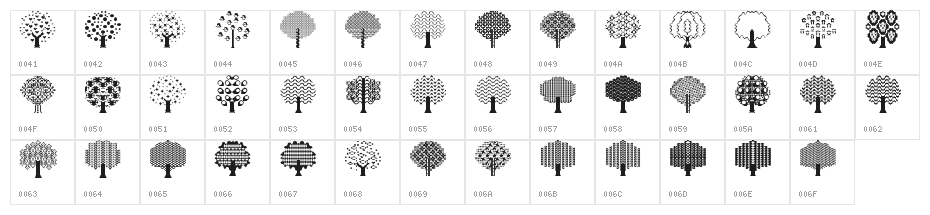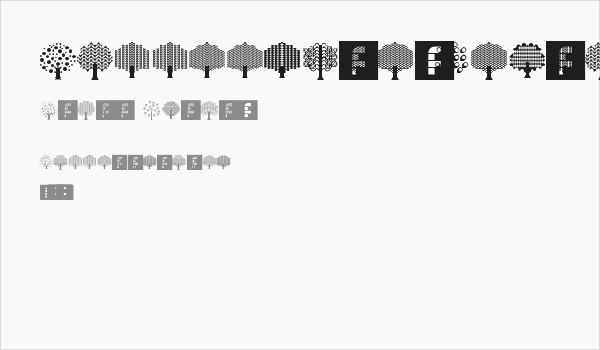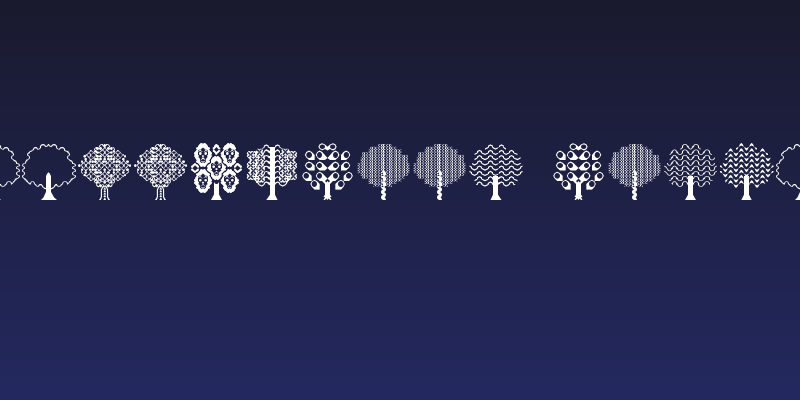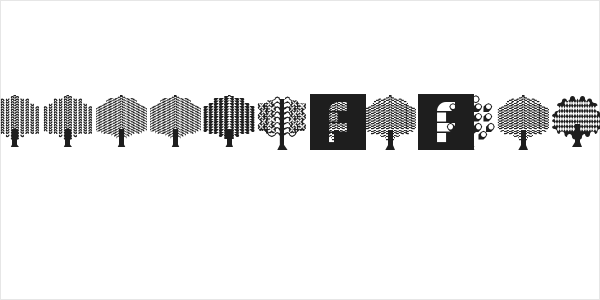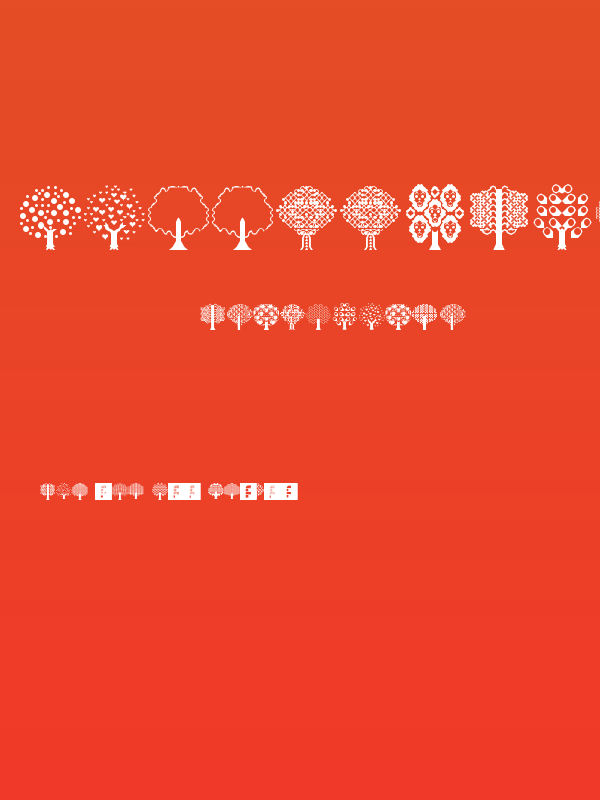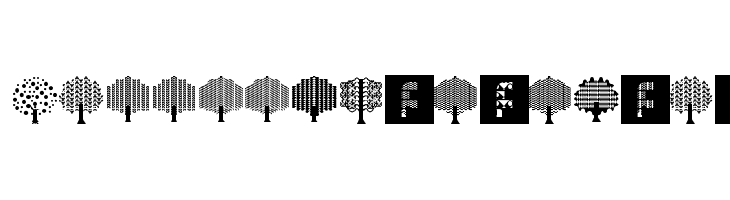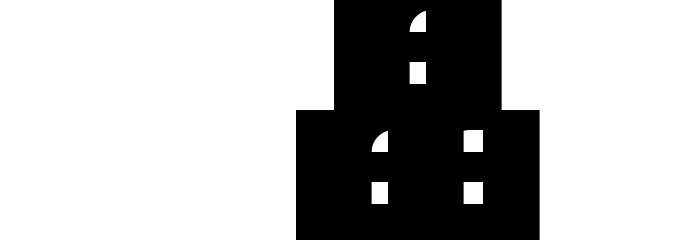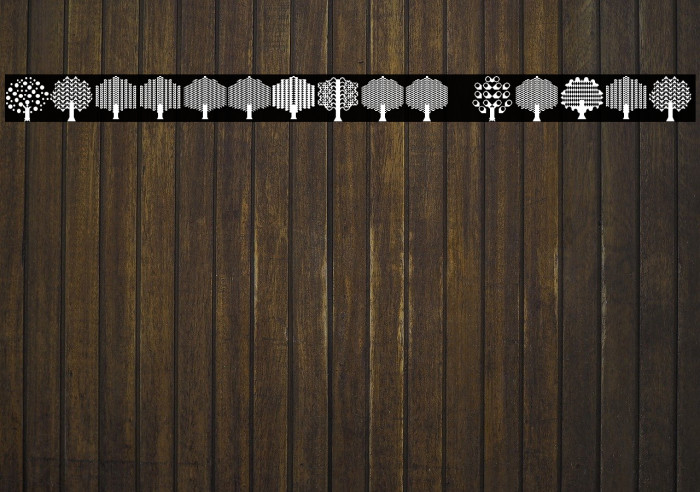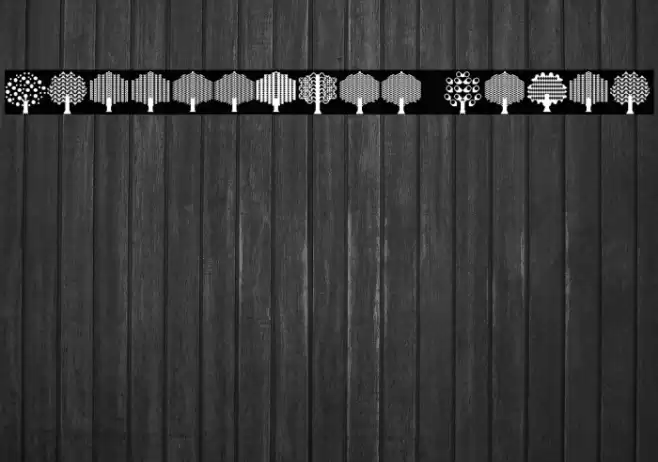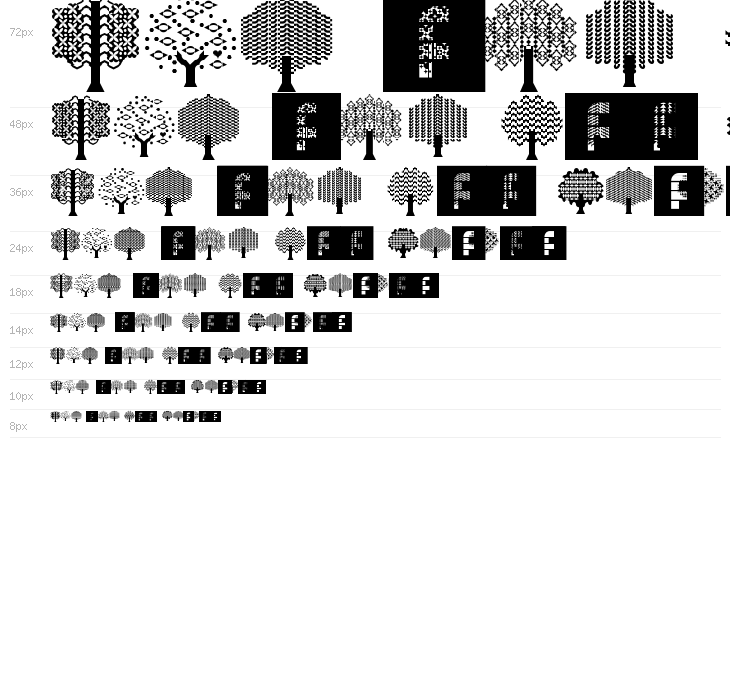
BalloonTrees Regular Font
| Gesamtstil | Decorative, Playful, Graphic |
| Anwendungsfall | Icons, Decorative elements, Logos, Themed illustrations |
| Vorgeschlagene Projekte | Nature-themed posters, eco-friendly branding, children's books, environmental infographics, decorative borders, and pattern design. |